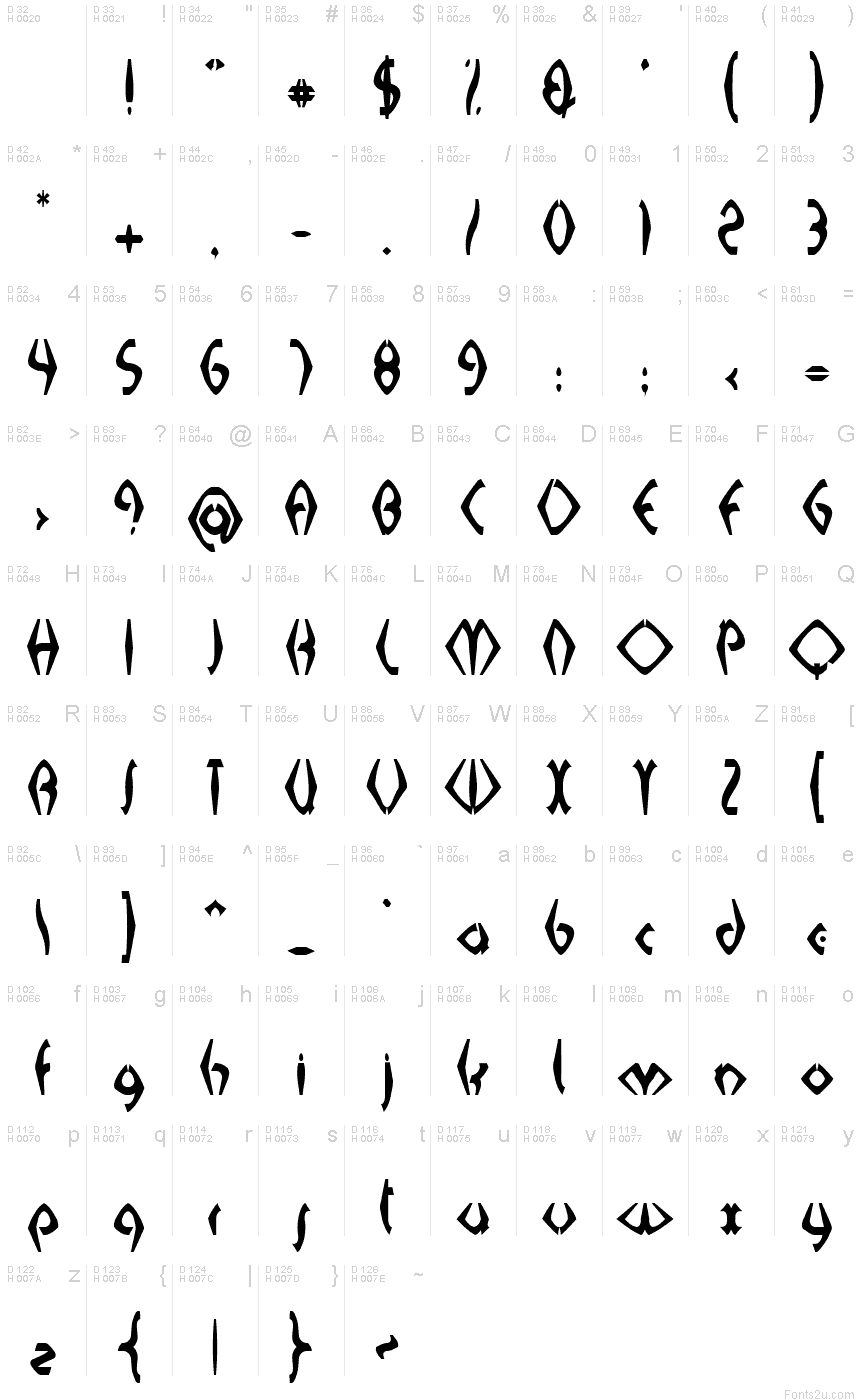
Sabomaster Uh! to darmowy, zniekształcony font displayowy o ostrym, niemal runicznym charakterze. Litery opierają się na spiczastych rombach, hakowatych pociągnięciach i nagłych cięciach, dzięki czemu kształty słów sprawiają wrażenie rzeźbionych i niepokornych, a nie gładkich czy równych.
To sprawia, że jest to naturalny wybór dla nagłówków plakatów, undergroundowych ulotek muzycznych, logotypów gier, okładek zinów i krótkiego brandingu, gdzie darmowy krój pisma potrzebuje dziwnego, ręcznie kutego sznytu. Najlepiej sprawdza się w krótkich formach, takich jak plansze tytułowe czy napisy na okładkach, ponieważ te kolczaste zawijasy i rozczłonkowane kształty budują nastrój, zanim jeszcze przeczytasz słowo.